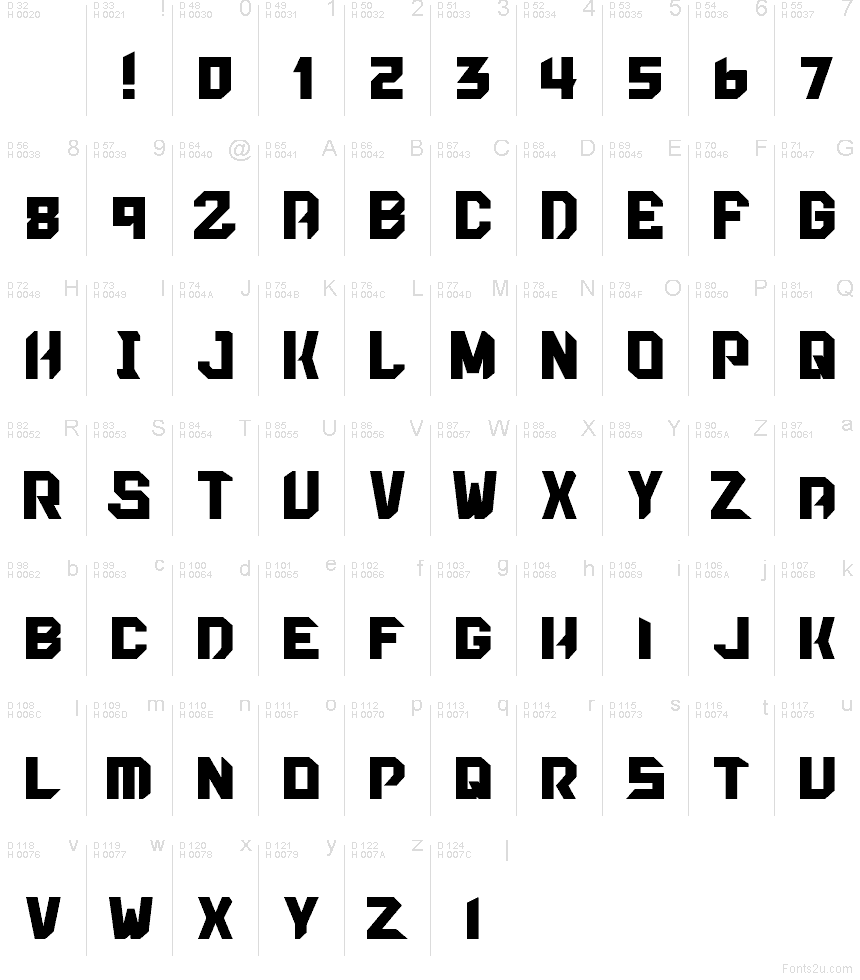
Smash Stadium Font
Smash Stadium - это бесплатный футуристический акцидентный шрифт с широкими блочными буквами, острыми углами и квадратными формами, которые напоминают вывески на аренах в стиле научной фантастики. Массивная геометрия разбавлена диагональными вырезами и узкими межбуквенными зазорами, что придает ему механический ритм без лишних украшательств.
Smash Stadium - это бесплатный шрифт для спортивного брендинга, игровых названий, заголовков на плакатах, промо-флаеров, логотипов и титров к трейлерам, где важна сильная, угловатая подача. Его жесткие формы и компактность отлично подходят, когда нужно, чтобы короткие слова, названия команд или рекламные тексты выглядели технично и агрессивно, а не мягко или декоративно.